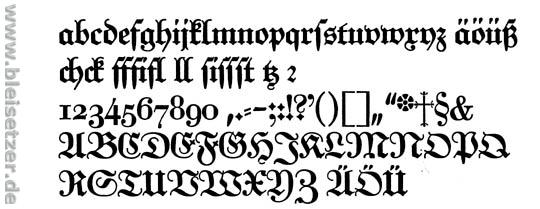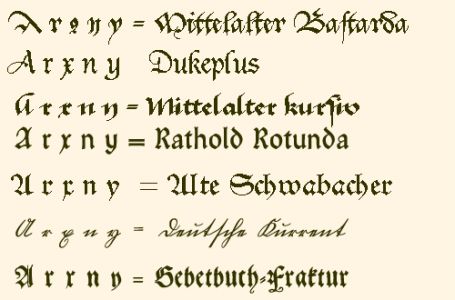
warum sieht die fraktur aus, wie sie aussieht?
so jetzt nochmal als extra thema, weil hier keiner auf meine frage eingegangen ist.
kann mir mal jemand erklären:
wieso das x wie ein r mit swash aussieht?
und wieso das y wie ein n mit swash aussieht?
und wie es es eigentlich damals zu dieser offenen A-form gekommen?
bei der breitkopf-fraktur ist das auch so.
ich will auch was lernen.
:?
die offene Form des Buchtstabens A kommt (so glaube ich, sprich reine Mutmaßung) von schlichter Ungenauigkeit. Während bei der Unziale das A noch in zwei Strichen durchgezogen wird, muss bei z.B. der Schwabacher drei mal angesetzt werden: Ein Schenkel öffnet sich und "schwimmt" weg. Wir reden über eine Zeit, als Schrift noch nicht definiert war.
Bitte verzeih das schlechte Bild, aber mein Scanner hier ist unter aller Kanone. Und bitte verzeih den Fehler im 3. Abstrich. Ich schreibe einfach zu selten.
Ich verstehe die Frage nicht ganz: Im Grunde könntest Du ja nach der Form jedes einzelnen Buchstabens fragen, die sich ja auch nicht einfach so ›erklären‹ lässt. Die Ähnlichkeiten betreffen ja auch nicht nur die von Dir genannten Buchstaben. Traditionell verteufelt ähnlich sind sich ja in vielen Gebrochenen:
r und x
n und y
aber auch:
k und t
n und u
b und v
o und v
f und s
und nicht nur:
A und U
sondern auch:
K und R
B und V
C und E
D und O
K und R
Ich glaube, man muss wirklich von der Handschrift her denken. In den älteren Textura-Schriften wurde auf extremes Gleichmaß geachtet, sie sind für uns heute sehr mühsam zu lesen. Buchstaben wie x, y und z, aber auch U [sic], J, W, Y und Z sind traditionell selten – es lag wohl nahe, einfach bestehende Buchstaben zu nehmen und diese zu ›markieren‹. Die Großbuchstaben wurden generell viel später normiert als die Kleinbuchstaben, hier haben sich traditionell mehr Varianten erhalten – muss nicht Nachlässigkeit sein, kann einfach auf eine erhaltene (Schreiber-)Variante zurückgehen.
... die offene Form des Buchtstabens A kommt (so glaube ich, sprich reine Mutmaßung) von schlichter Ungenauigkeit. Während bei der Unziale ...
Beginnt diese Form des A nicht erst bei der Rotunda, wenn man von der Entwicklung des a mit einem großen und hohen Bogen an der linken Seite bei der Halbunzialen absieht und daraus vielleicht eine Variation des großen A aus der kursiven gotischen Buchschrift?
Die Unziale war im 5. Jhdt. Danach kam die Halbunziale (ab 6. Jhdt, keine reine Großbuchstabenschrift), dann merowingische, karolingische Minuskel (9. Jhdt), gotische Minuskel und Kursive ( 13. Jhdt), Textura (14. Jhdt), Gotico-Antiqua (15. Jhdt). Daneben die kursiven Buchschriften. Im habe mich jetzt auf unseren Raum beschränkt und nicht allzu detailliert aufgeführt.
Die Rotunda kam dann im 15. Jhdt, die Schwabacher als weniger künstlerisch ausgestaltete Volksdruckschrift entstand gegen Ende des 15. Jhdts. unter dem Einfluss der Rotunda. Zu Beginn des 16. Jahrhunderts wurde die Fraktur geschaffen, die in ihrer Formgebung durch die in der kaiserliche Kanzlei üblich gewordene verzierte Kurrentschrift (also vom flüssigen Schreiben) bestimmt war.
(Benutzte Quelle: „Unsere Schrift“ Eine Einführung in die Schriftkunde von Heribert Sturm)
Hier ein paar schnell zusammengestellte Schriften ab dem Mittelalter zum Vergleichen der Buchstaben, natürlich zu beachten, dass wahrscheinlich bei der Digitalisierung auch Veränderungen vorgenommen und manches angepasst wurde:
Tolle Übersicht, Tholan! Ich denke, man sieht an ihnen schön, dass:
a) bei den Minuskeln viel größere Regelmäßigkeit herrscht, und dass
b) bei den (früher u. U. noch separat verzierten) Großbuchstaben generell größere Varianten sich erhalten haben
c) die Vermutung sich erhärtet, dass es bei den Minuskeln mindestens so sehr auf Gleichmaß ankam als auf Unterscheidung; die seltenen Buchstaben x und y scheinen – eventuell nachträglich? – auf bestehenden aufgebaut worden zu sein.
Das kann ja vielleicht auch ökonomische Gründe haben: Vielleicht konnte man Punzen einsparen, indem man z. B. einem r einfach noch einen Quer- oder einen Abstrich anfügen? Aber dies ist reine Vermutung…
bei der breitkopf-fraktur ist das auch so.
ich will auch was lernen.
Macht ja nix, aber das ist die Unger-Fraktur …
es gibt ein altes buch aus den 80ern, ich glaube es heisst "schriften zeichnen", in dem für fast alle verbreiteten schrifttypen (von gebrochenen über antiquas bis zu engen und normalen serifenlosen) erklärt wird, wie sie mit der feder gezeichnet werden. das wird zwar nicht deine frage beantworten, aber wenn du am schriftenzeichnen interessiert bist ist es doch ein ganz interessantes büchlein (und kostete auch nur 20€ oder so).
ich habe das buch nach einer empfehlung auf typophile in einem antiquariat gefunden (über ZVAB). leider ist der karton mit allen designbüchern momentan auf einem fremden dachstock parkiert (zügeln und so), ich werde aber in den nächsten 2-3 wochen sicher nochmal da hochsteigen um sachen zu holen - wenn du willst kann ich dir dann den genauen namen und die autoren raussuchen.
die endgültige Form von x und y in der Welt der Gebrochenen.
*Das Original befindet sich in Augsburg, die Faksimile-Ausgabe
erschien im Insel-Verlag mit einem Begleittext von Carl Wehmer.
Schon klar, Tholan, das hatte ich nicht behaupten wollen… Ich nehme an, Du hast es (auch) öfters mit alten Handschriften oder Drucken zu tun?